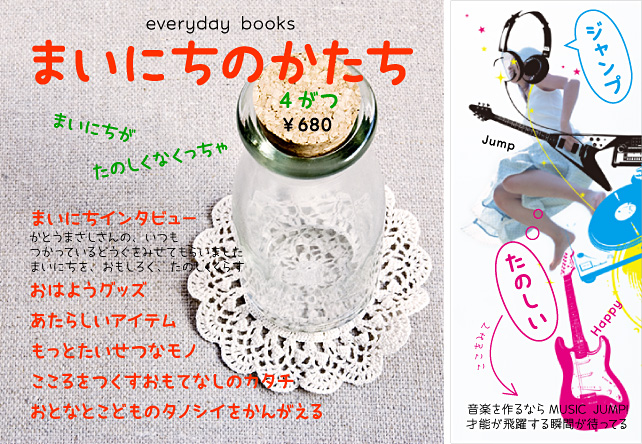
手書き風日本語フォントHaruka(はるか)フォントとは 「はるか」は女性のキュートな手書き文字を参考にして作成した書体です。近年の女性の文字のクセを取り入れつつもデザインとして統一感のあるフォント。自分らしく自由にイキイキと活動している。そんな元気な女性像をイメージしています。ひらがな、カタカナ、アルファベット、記号のみの書体ですが、一般的な丸ゴシックの漢字と組み合わせて使える、最適な線の太さになっています。  |